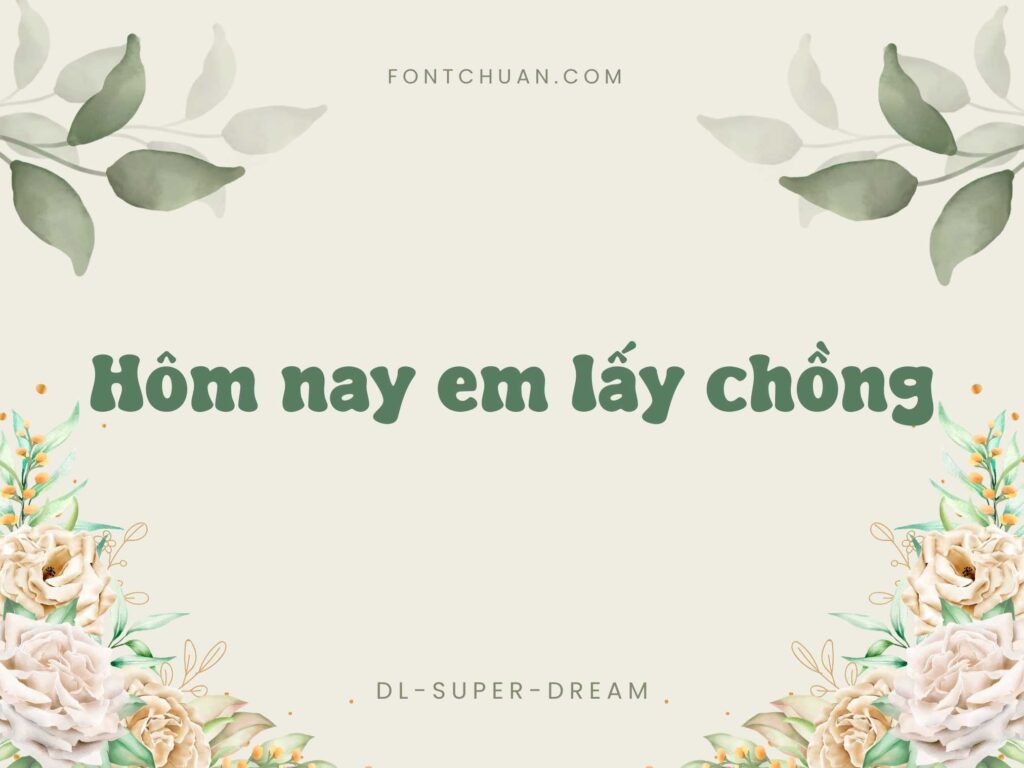
Font DL Super Dream Việt Hóa
Super Dream là một font chữ hiển thị phong cách retro, mang đến cảm giác vui tươi và năng động cho các thiết kế. Được tạo ra bởi nhà thiết kế fsuarez913, font này kết hợp giữa nét đậm và các đường cong mềm mại, tạo nên sự thu hút đặc biệt. Với sự Việt hóa của Tduy, Super Dream hỗ trợ đầy đủ các ký tự tiếng Việt, giúp người dùng dễ dàng áp dụng trong các dự án thiết kế đa ngôn ngữ. Thành viên của Font Chuẩn đã sưu tầm và chia sẻ font này nhằm đáp ứng nhu cầu của cộng đồng thiết kế.
Về đặc điểm thiết kế, Super Dream sở hữu 433 glyphs với 454 ký tự, bao gồm cả chữ hoa, chữ thường, số và các ký tự đặc biệt. Font này đặc biệt phù hợp cho các dự án thiết kế như poster sự kiện, thương hiệu retro, tiêu đề nổi bật và các ấn phẩm quảng cáo cần sự nổi bật và cá tính. Ngoài ra, Super Dream cũng thích hợp cho các sự kiện như lễ hội, sinh nhật, Valentine và Trung thu, mang lại không khí vui vẻ và ấm áp. Trong lĩnh vực ngành nghề, font này được ứng dụng rộng rãi trong quảng cáo, thiết kế đồ họa, thời trang và truyền thông, góp phần tạo nên sự độc đáo và thu hút cho các sản phẩm và thương hiệu.